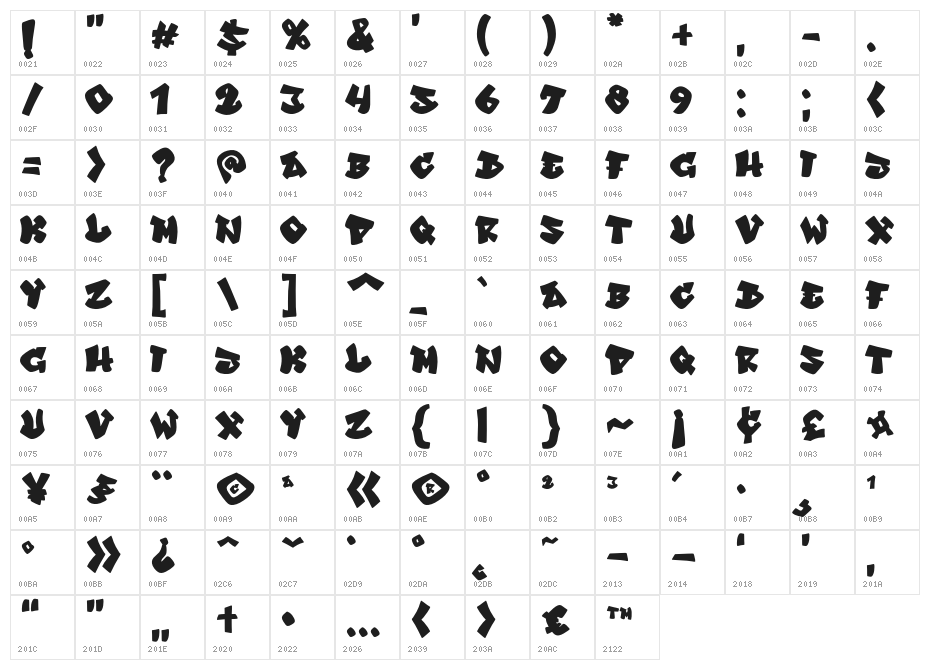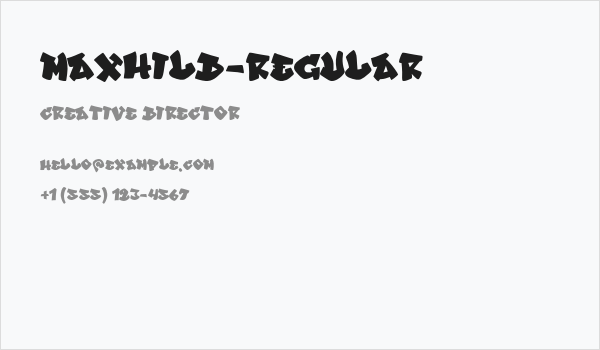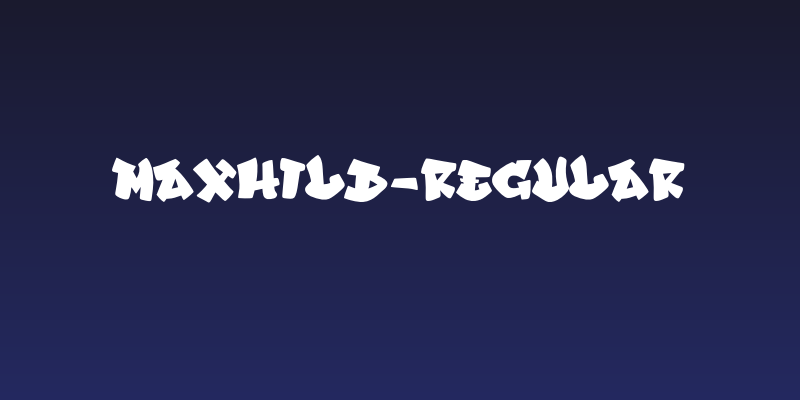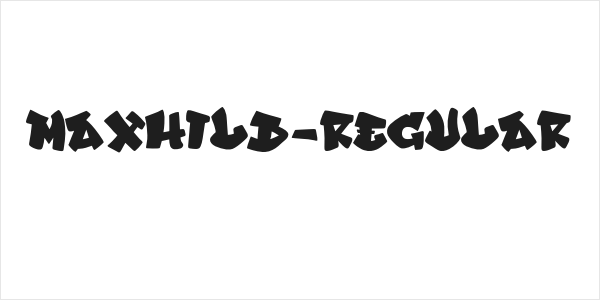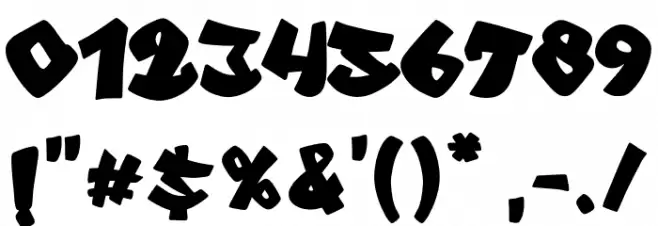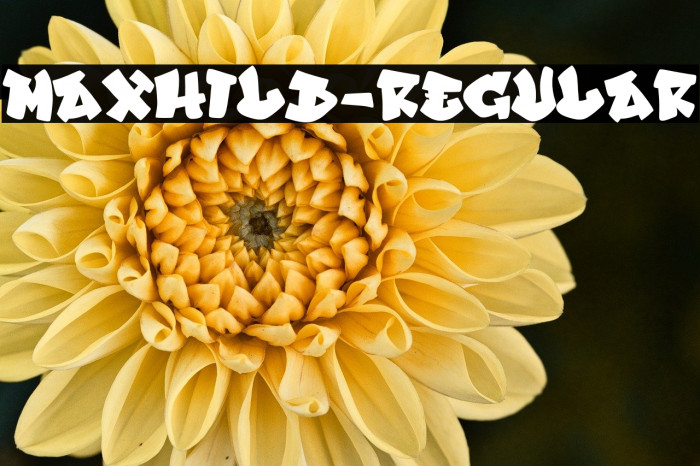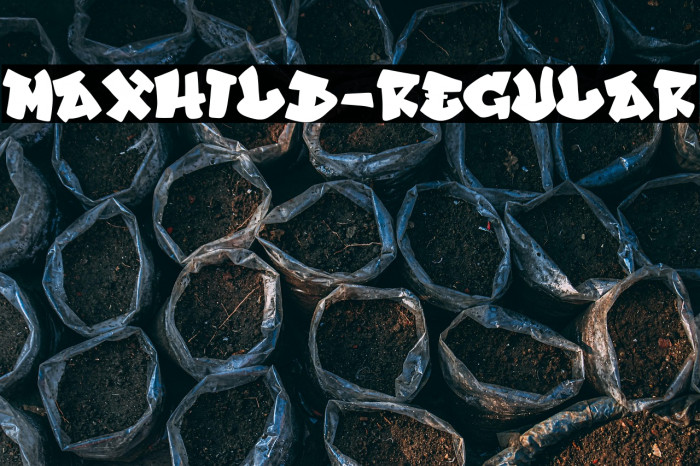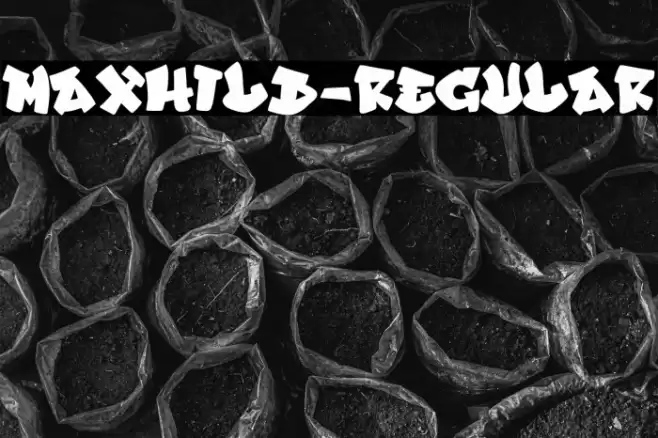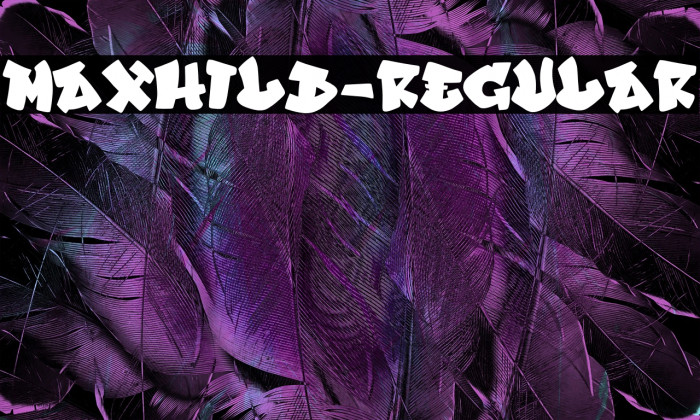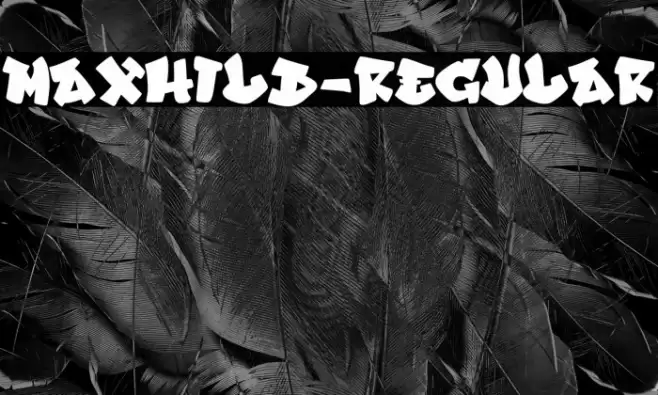
Maxhild-Regular Font
MAXHILD-REGULAR MAIUSCOLE
MAXHILD-REGULAR MINUSCOLO
MAXHILD-REGULAR ALTRI CARATTERI
| Nome | Maxhild-Regular |
| Famiglia di caratteri | Maxhild |
| Stile generale | Playful, Cartoonish, Energetic |
| Progetti proposti | Ideal for comic books, children's books, playful branding, and eye-catching posters. |